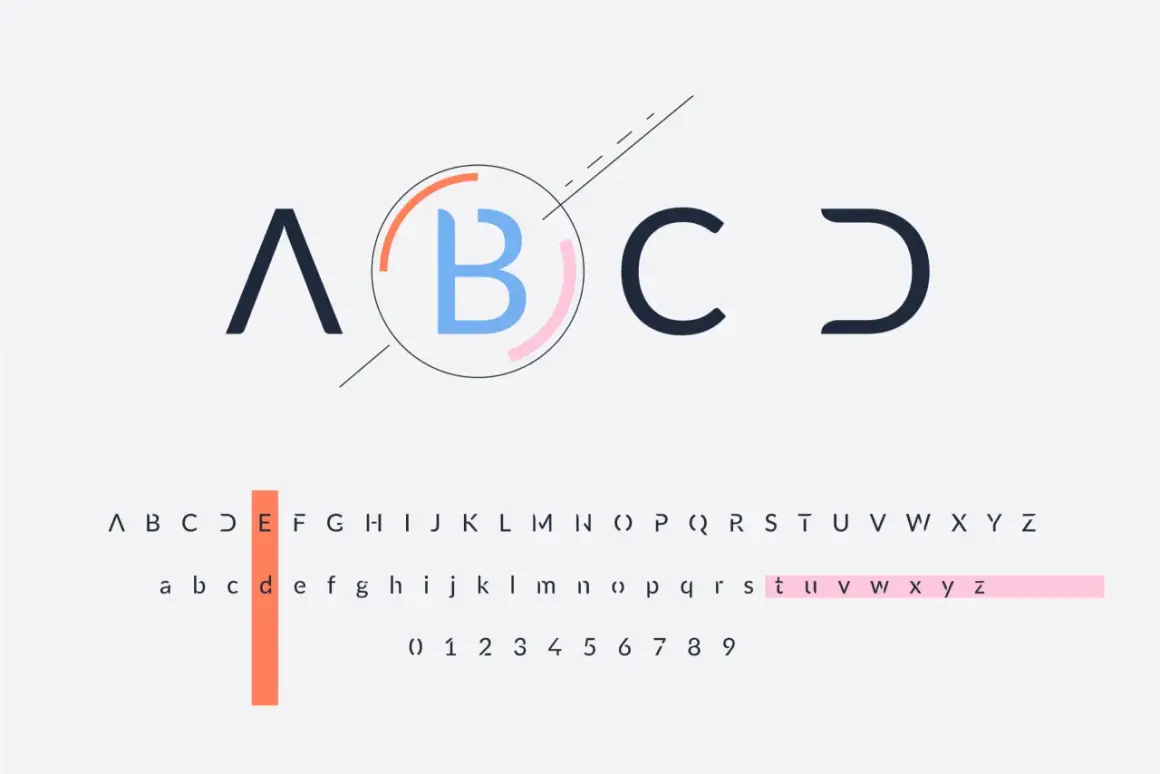
Dobra kompozycja tekstu decyduje o tym, czy odbiorca czyta z przyjemnością, czy męczy się już po pierwszym akapicie. W praktyce typografia jest jednym z tych elementów, które potrafią podnieść jakość plakatu, albumu, ulotki albo strony internetowej bez dodawania żadnych ozdobników. Poniżej pokazuję, co naprawdę wpływa na czytelność, jak dobierać krój pisma do konkretnego projektu i czego unikać, gdy tekst ma dobrze wyglądać także po wydruku.
Najważniejsze zasady, które od razu poprawiają czytelność tekstu
- Najpierw ustaw hierarchię: tytuł, śródtytuły, podpisy i tekst główny muszą mieć wyraźnie różne poziomy ważności.
- Do dłuższych bloków wybieraj prosty krój o dobrej czytelności, a ozdobne fonty zostaw na akcenty.
- Dbaj o interlinię, odstępy i długość wiersza, bo to one najszybciej poprawiają komfort czytania.
- W materiałach drukowanych sprawdzaj efekt na próbce, a nie tylko na ekranie.
- Im bardziej pracuje zdjęcie, tym spokojniejszy powinien być skład tekstu.
Kiedy typografia pracuje na treść, a kiedy ją osłabia
Dobry skład nie ma się sam prezentować, tylko prowadzić wzrok. Gdy układ jest przemyślany, odbiorca od razu wie, co czytać najpierw, gdzie zatrzymać się na chwilę i które informacje są pomocnicze. Tego właśnie oczekuję od każdego projektu: tekst ma wspierać przekaz, a nie z nim konkurować.
W praktyce widzę dwie skrajności. Pierwsza to projekty „przeładowane” różnymi krojami, efektami i ozdobami, które robią wrażenie przez kilka sekund, ale szybko męczą. Druga to skład zbyt surowy, bez hierarchii i oddechu, przez co nawet wartościowa treść traci wyrazistość. Najlepsze rozwiązania zwykle leżą pośrodku: są proste, konsekwentne i dopasowane do medium.
Jeśli projekt ma działać w druku, szczególnie ważne stają się kontrast, rozmiar i proporcje między tekstem a obrazem. To prowadzi naturalnie do pytań o konkretne elementy składu, które naprawdę robią różnicę.
Najważniejsze elementy składu, które naprawdę widać
Na etapie projektowania najłatwiej skupić się na samym kroju pisma, ale w praktyce o jakości decyduje cały zestaw decyzji. Ja zawsze patrzę na tekst jak na system, nie pojedynczy font.
Krój i stopień pisma
Krój pisma powinien pasować do długości tekstu i charakteru projektu. W dłuższych treściach lepiej działają proste, stabilne kroje o spokojnym rysunku. Ozdobne rozwiązania zostawiam do nagłówków, krótkich cytatów albo materiałów, które mają bardziej ekspresyjny ton. W druku tekst główny najczęściej mieści się w zakresie 9-11 pt, a podpisy pod zdjęciami zwykle potrzebują osobnej, nieco mniejszej skali.
Interlinia, światło i kerning
Interlinia to odstęp między wierszami, a kerning reguluje przestrzeń między konkretnymi parami znaków. Brzmi technicznie, ale efekt widać od razu: zbyt ciasny skład robi się ciężki, a zbyt luźny traci rytm. W dłuższych blokach tekstu dobrze sprawdza się interlinia na poziomie około 120-145% stopnia pisma, bo daje oczom oddech bez rozbijania akapitów.Przeczytaj również: Po co 3 aparaty w telefonie? Odkryj ich niesamowite możliwości
Wyrównanie i długość wiersza
Długość wiersza ma większe znaczenie, niż wiele osób zakłada. Przy zbyt szerokiej kolumnie czytelnik gubi rytm, a przy zbyt wąskiej tekst zaczyna skakać. W materiałach drukowanych dobrze celować mniej więcej w 45-75 znaków w wierszu, choć dokładna wartość zależy od formatu i rodzaju treści. Ja najchętniej testuję to na wydruku roboczym, bo ekran potrafi zmylić.
Gdy te podstawy są ustawione dobrze, łatwiej wybrać samą rodzinę kroju do konkretnego projektu.
Jak dobrać krój do projektu drukowanego
Nie ma jednego uniwersalnego fontu, który rozwiązuje wszystko. Wybór zależy od tego, czy projekt ma być elegancki, nowoczesny, informacyjny, czy bardziej artystyczny. Poniżej zestawiam najczęściej spotykane grupy krojów i ich praktyczne zastosowania.
| Rodzina kroju | Najlepsze zastosowanie | Co daje | Na co uważać |
|---|---|---|---|
| Szeryfowy | Dłuższe teksty, albumy, katalogi, eleganckie druki | Spokojny rytm i dobre prowadzenie wzroku | W bardzo małych stopniach może stracić klarowność |
| Bezszeryfowy | Nagłówki, layouty nowoczesne, podpisy, infografiki | Porządek, prostota i czytelność na ekranie oraz w druku | Przy długich akapitach bywa chłodny, jeśli nie ma dobrego rytmu |
| Display | Okładki, plakaty, krótkie hasła | Silny charakter i rozpoznawalność | Nie nadaje się do długich bloków tekstu |
| Skryptowy | Zaproszenia, branding premium, delikatne akcenty | Wrażenie ręczności i lekkości | Łatwo przesadzić i obniżyć czytelność |
| Monospace | Specyfikacje, dane techniczne, cytaty stylizowane | Równy rytm i mocny, techniczny charakter | W długich tekstach szybko męczy |
W praktyce najbezpieczniejszy zestaw to jeden krój do tekstu głównego i drugi do nagłówków. Jeśli potrzebujesz trzeciego, ma on już zwykle rolę czysto akcentującą. To podejście dobrze działa zarówno w katalogach fotograficznych, jak i w materiałach reklamowych, gdzie zdjęcie ma pierwszeństwo, a litery mają je uzupełniać.
- Oceń, czy kroje nadal wyglądają dobrze po konwersji do PDF i po wydruku testowym.
- Zostaw sobie jedną wersję z większym oddechem, jeśli projekt ma iść na papier matowy albo mocno absorbujący światło.
Na koniec zostaje rzecz najprostsza, a często pomijana: dopasowanie składu do tego, jak odbiorca faktycznie będzie czytał materiał. Jeśli ma oglądać zdjęcia i tylko zatrzymywać się na podpisach, tekst powinien być oszczędny. Jeśli ma czytać dłuższy opis, musi mieć wyraźną hierarchię, wygodny rytm i spokojny krój. Właśnie wtedy skład zaczyna pracować na treść, a nie przeciwko niej.